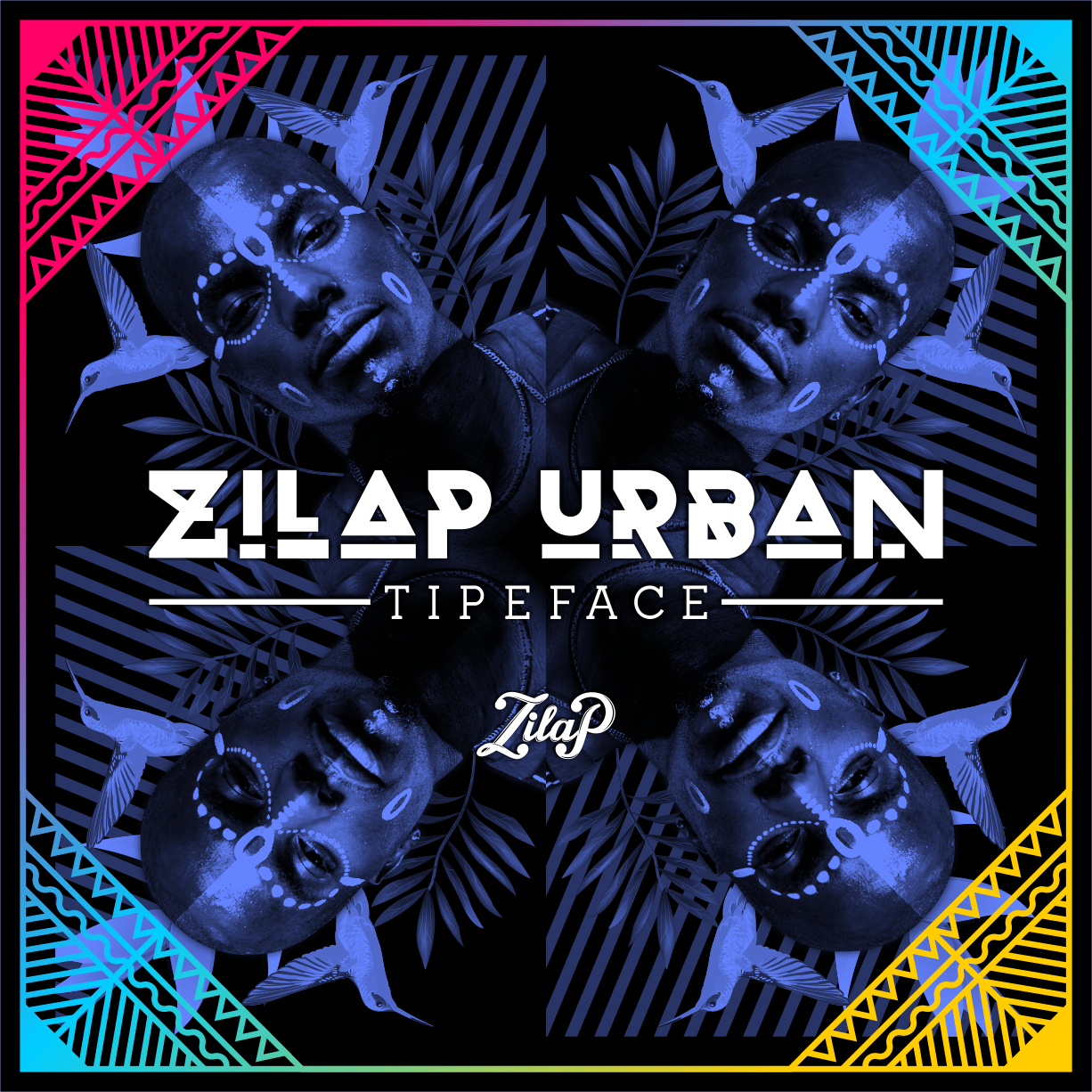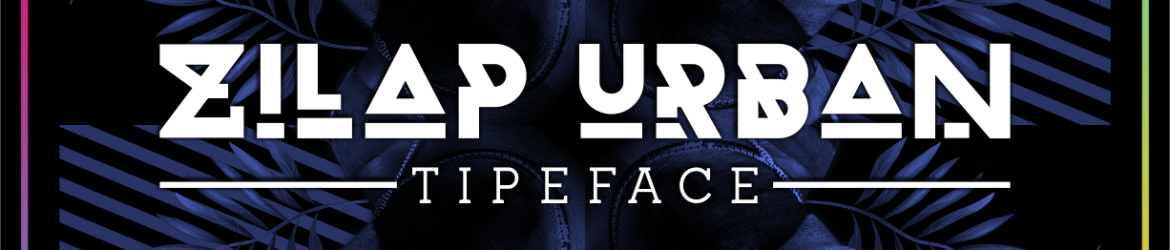
Zilap Urban Font – Download Grátis
Zilap Urban é uma elegante fonte dedicada ao universo vibrante e dinâmico do gênero urbano musical. Inspirada nos ritmos pulsantes que movem as pistas de dança, esta tipografia urbana se encaixa perfeitamente em nossa contemporaneidade, trazendo à vida os sons da cultura popular. Com linhas agudas e formas retangulares que remetem às letras digitais dos DJs e beatmakers, Zilap Urban é perfeita para criar designs gráficos vibrantes. Perfeito para aplicar na arte urbana, logotipos de marcas ou qualquer projeto visual em movimento, esta fonte urbanizada é a escolha ideal para capturar o espírito da música moderna e sua efervescente atmosfera. Como uma nova voz no mundo das tipografias decorativas, Zilap Urban surge como a solução perfeita para expressar os sons do futuro.